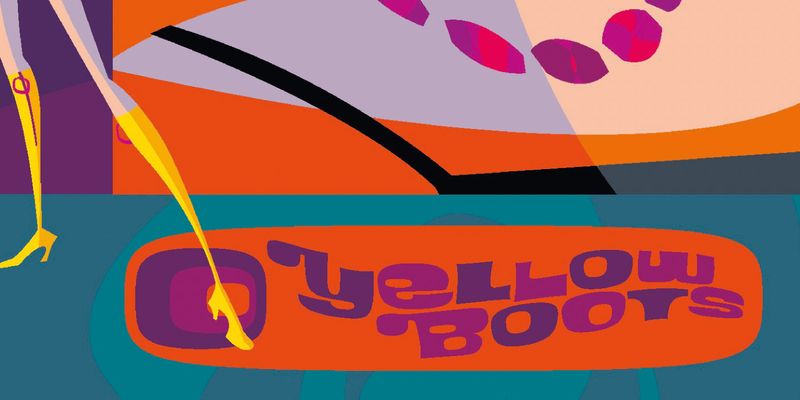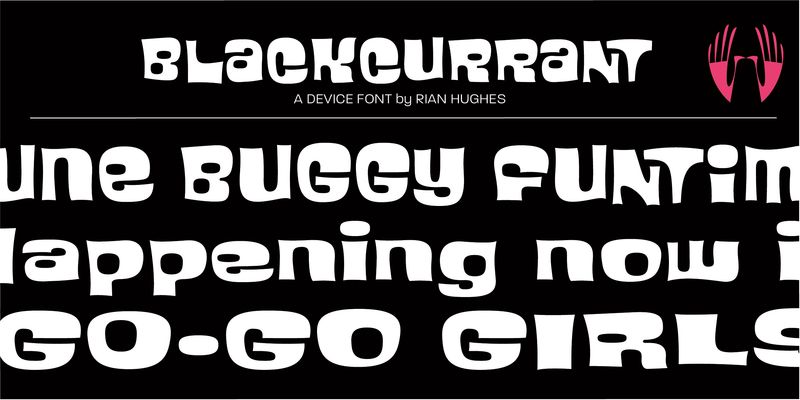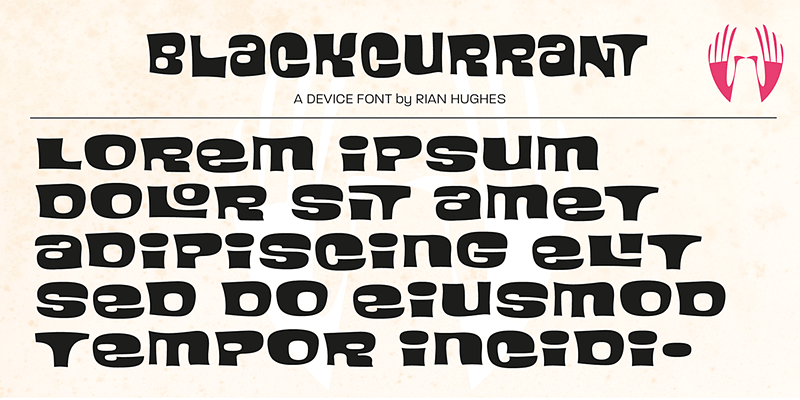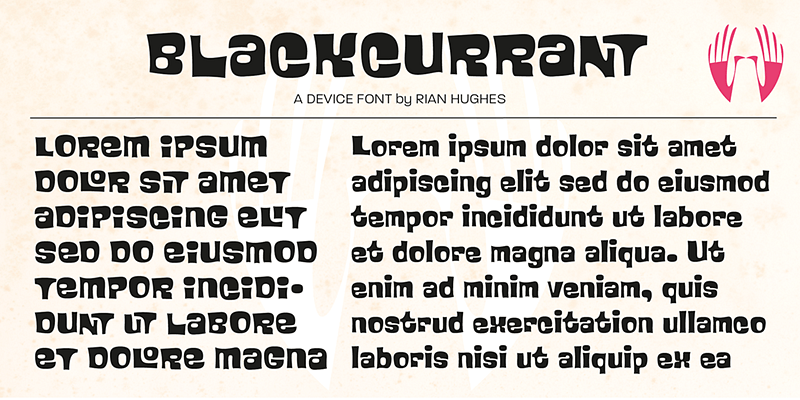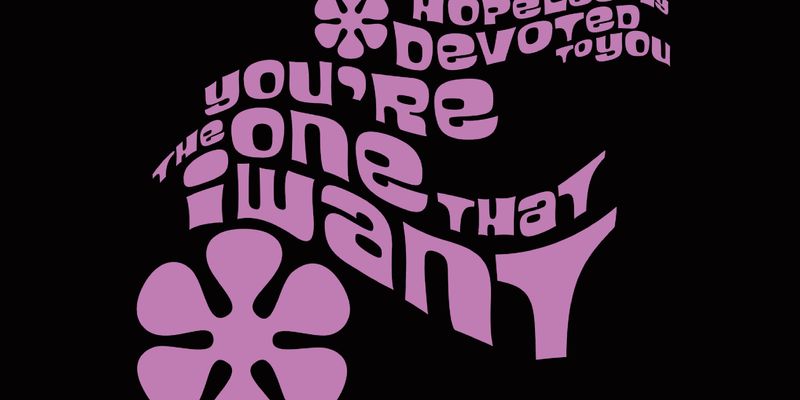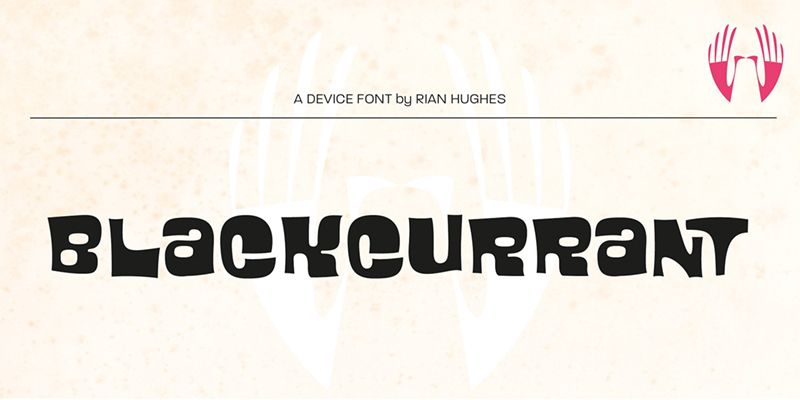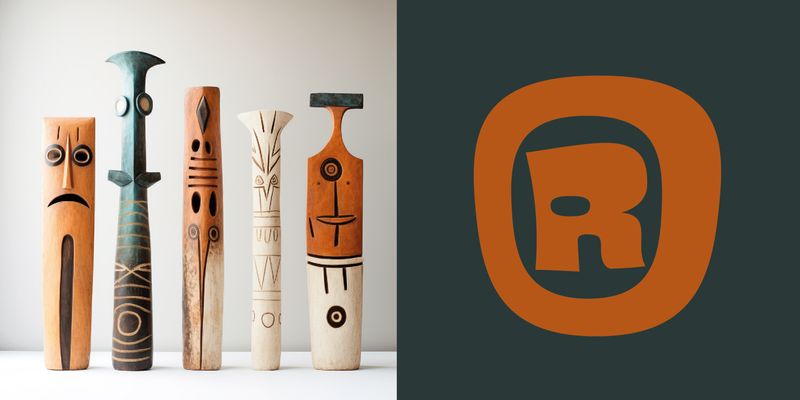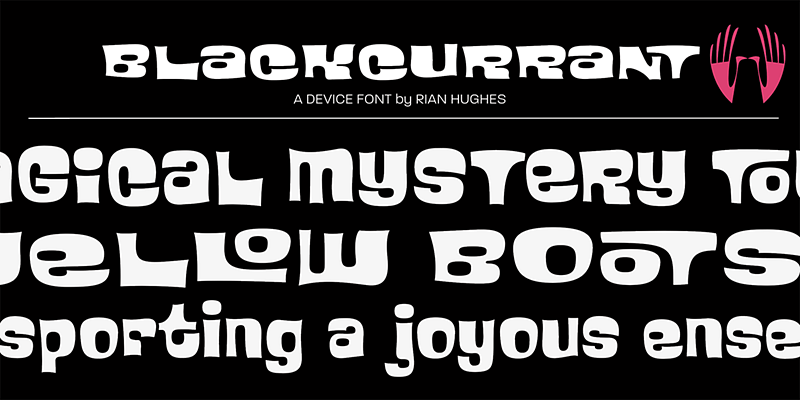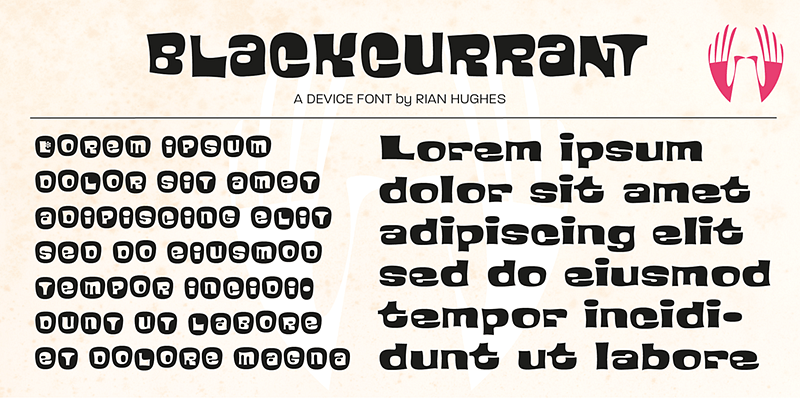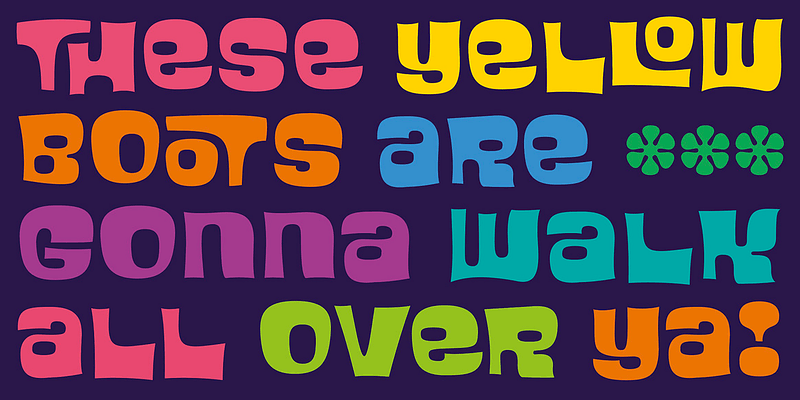
Eine fröhliche Schriftart für Überschriften – mit einem funky und hippen Touch.
Schrift, Design und Bilder stammen vom englischen Illustrator und Typografen Rian Hughes.